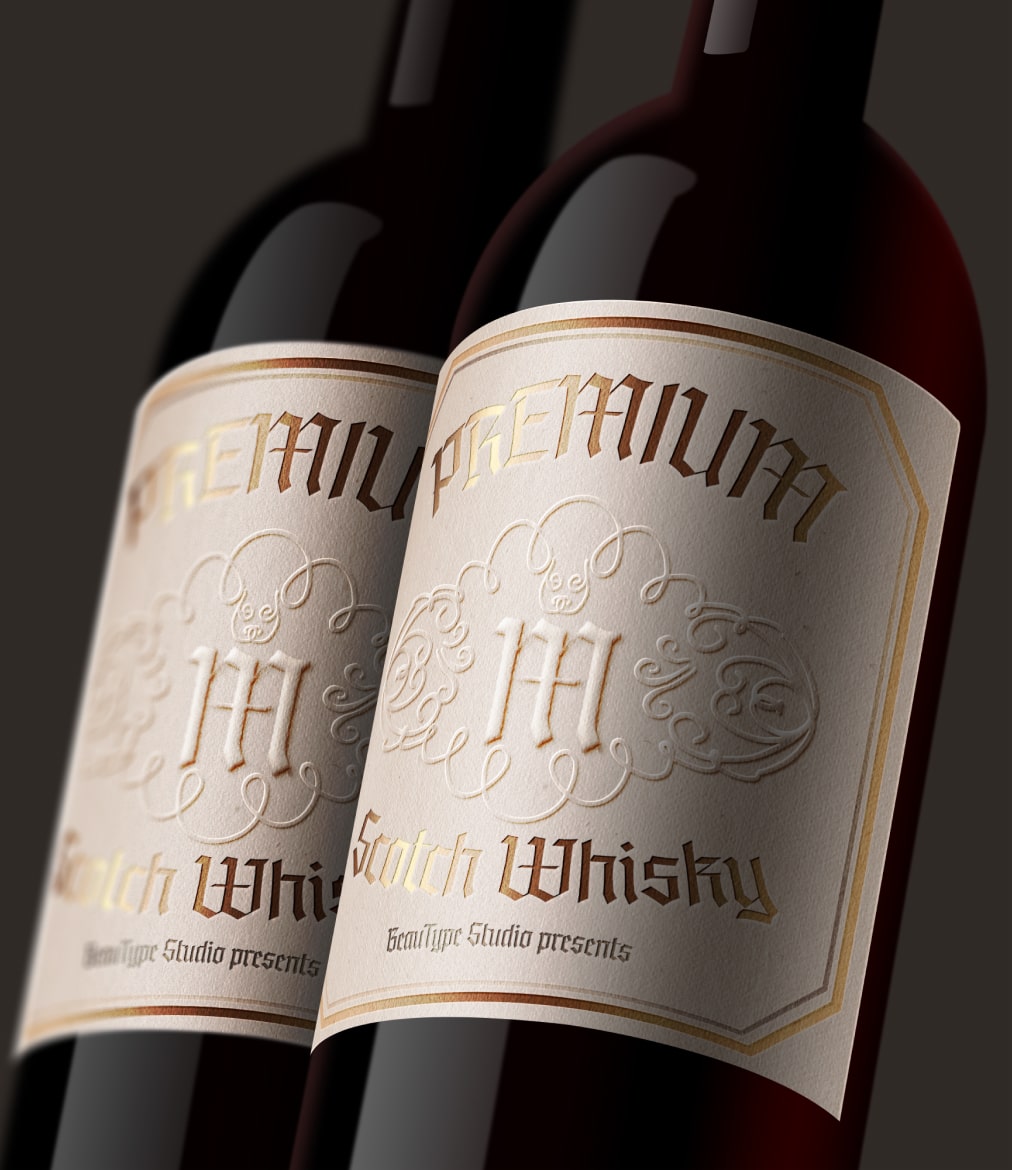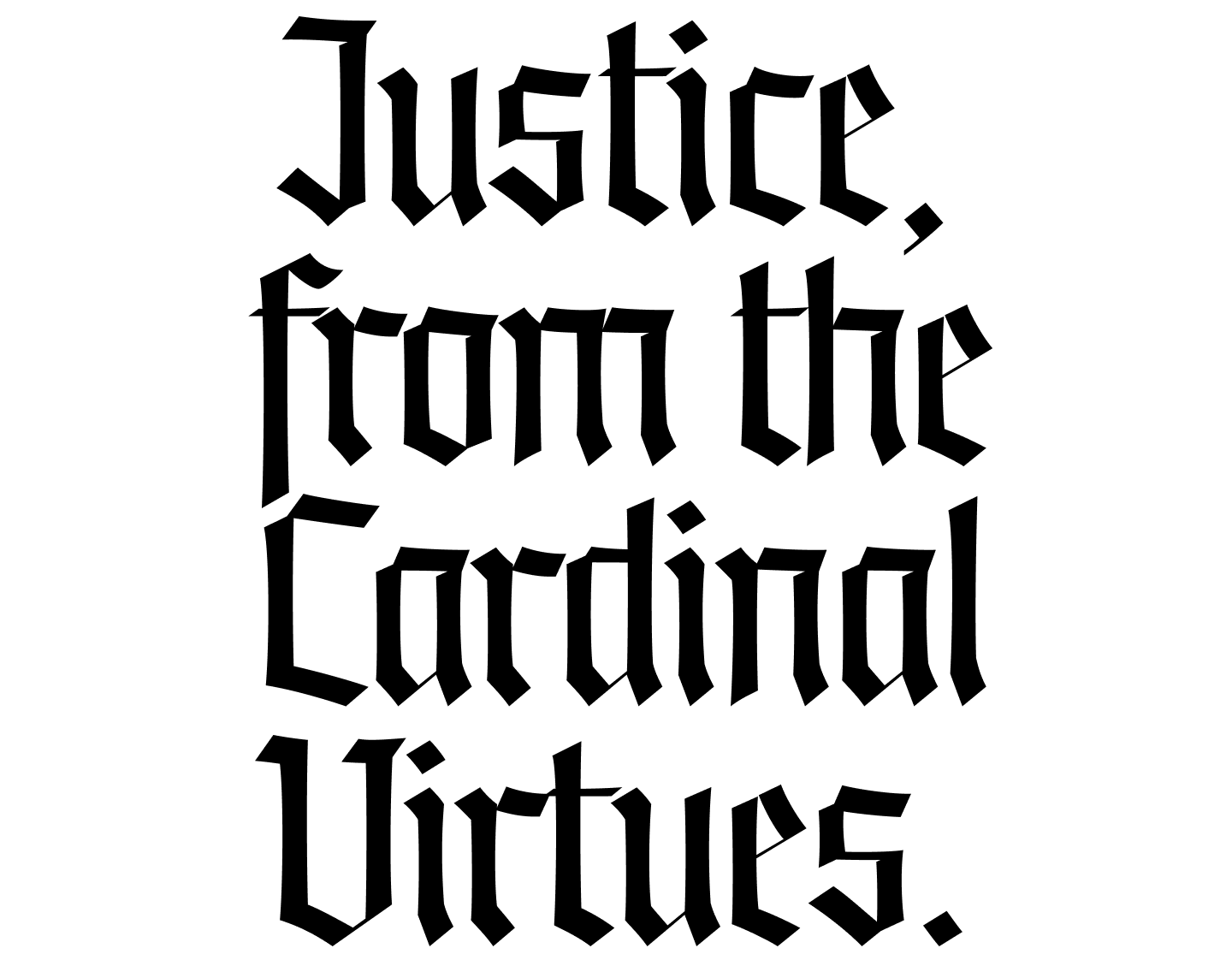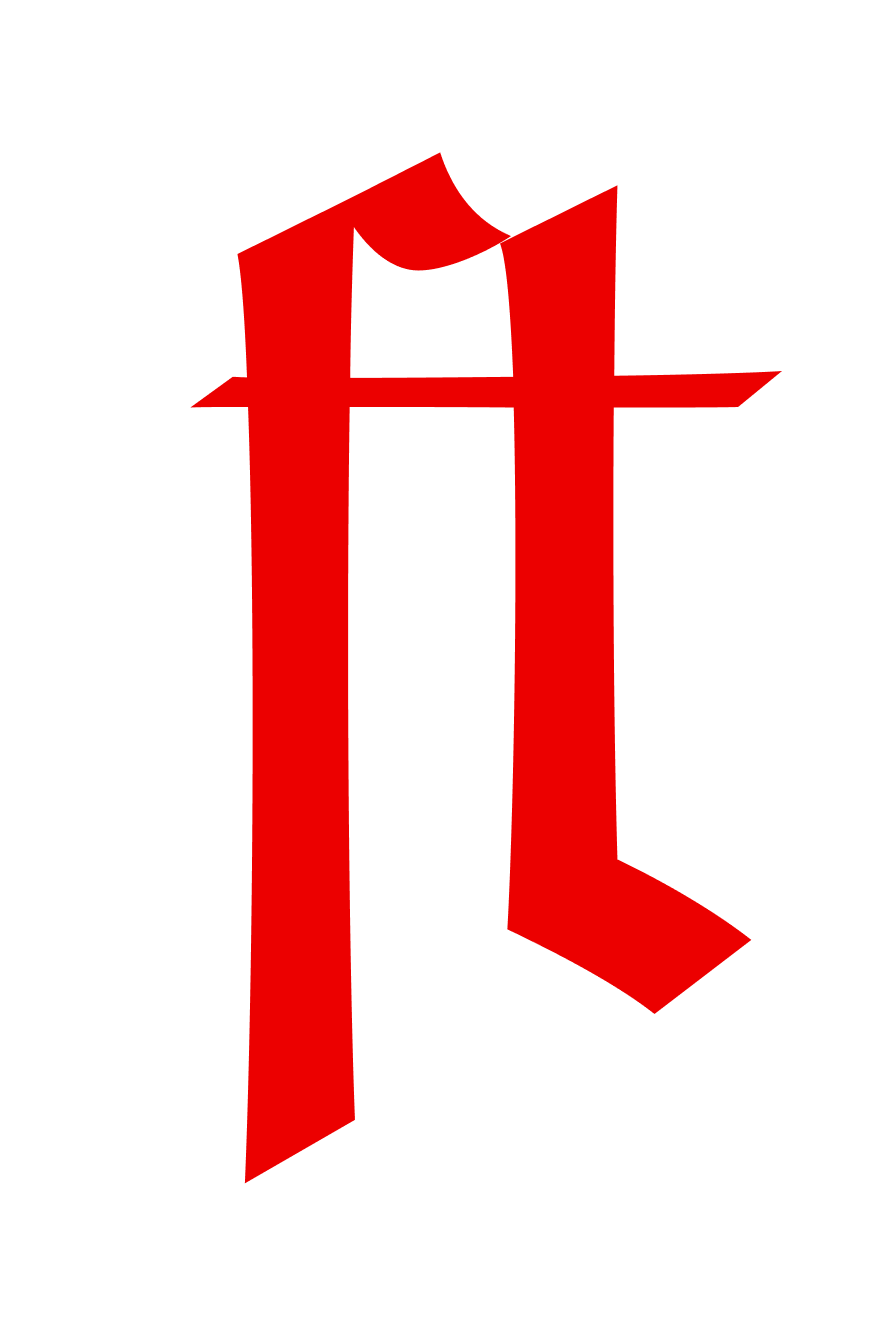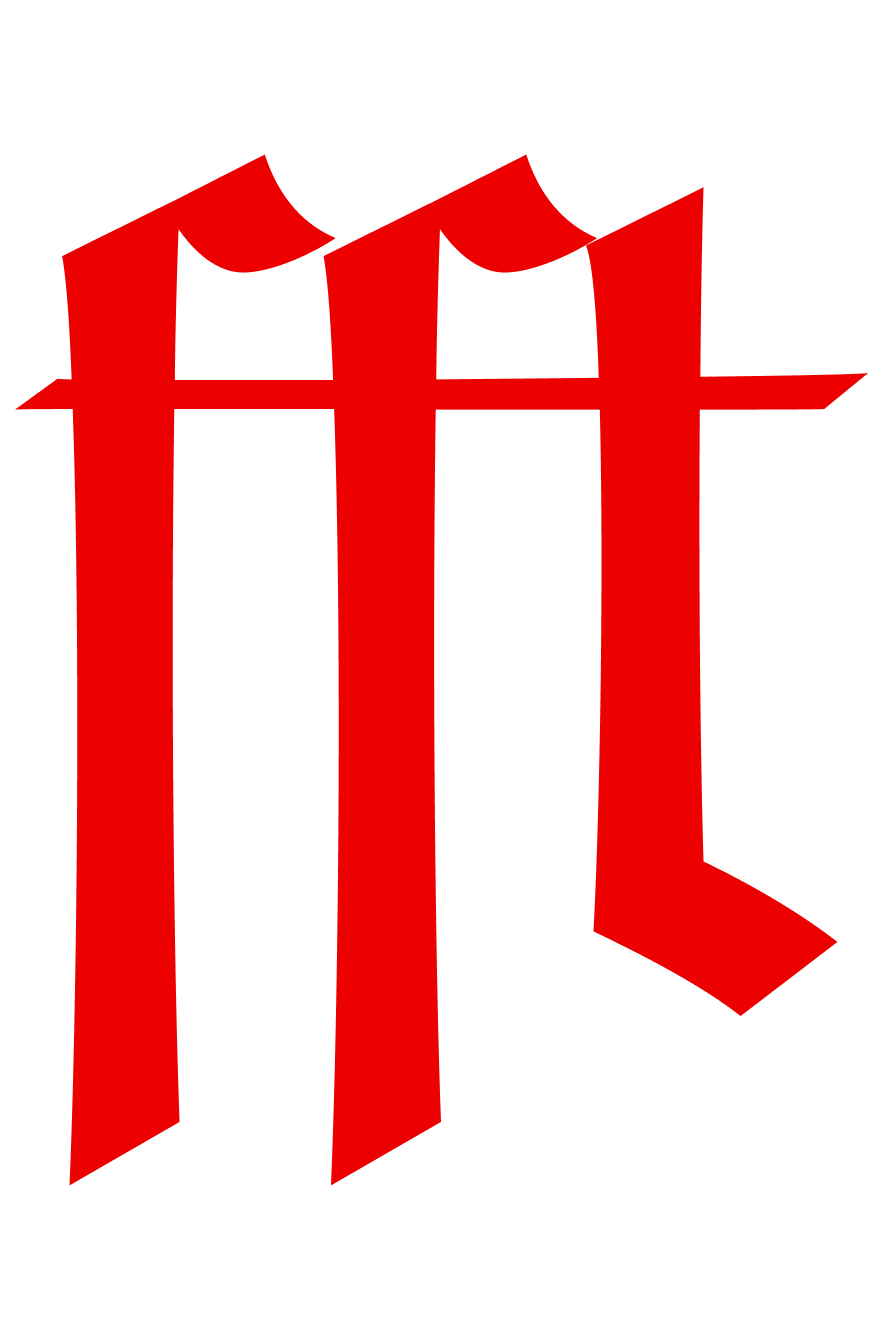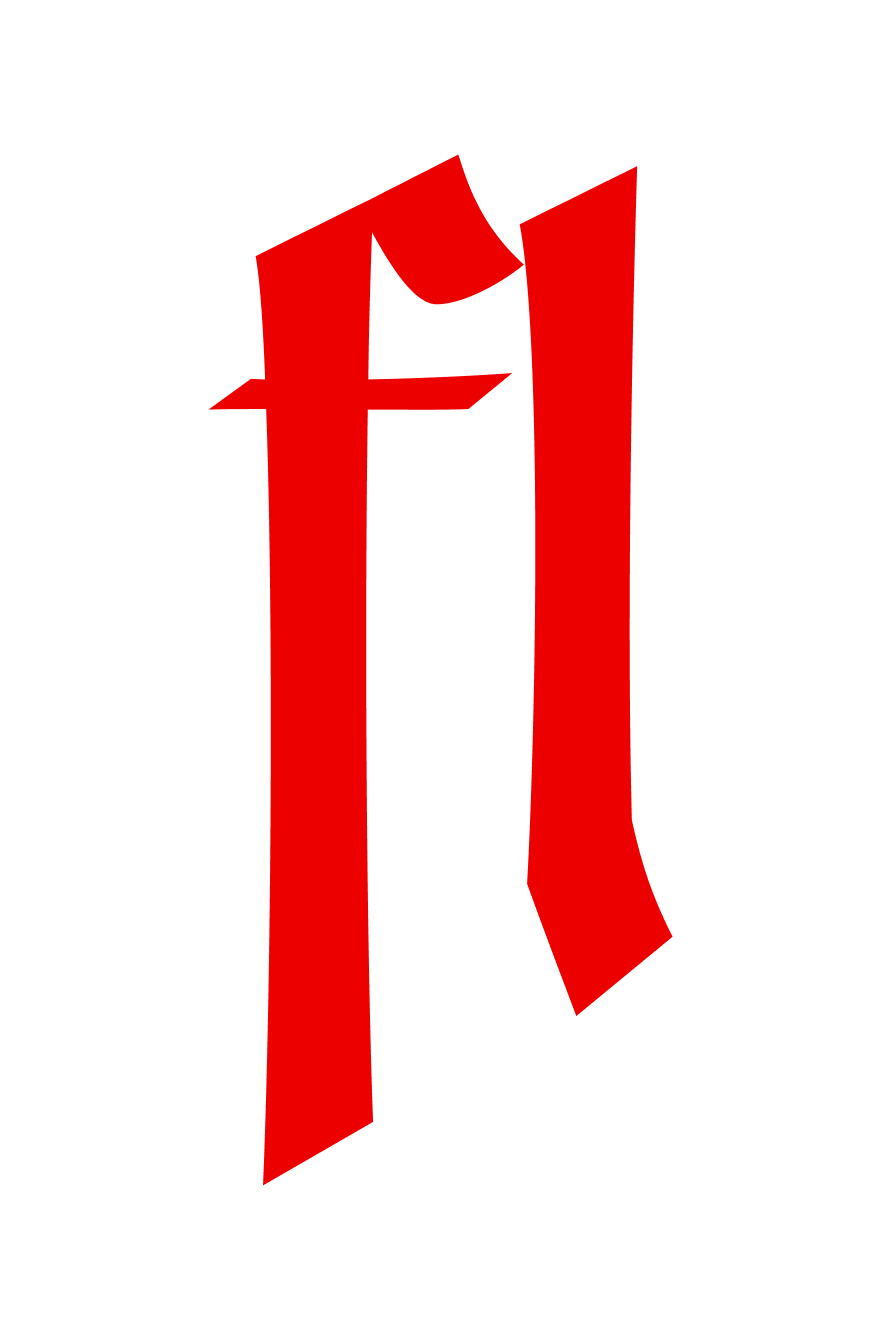
Gothic allure
Khi nghiên cứu các văn bản Kinh Thánh thời Trung Cổ, chúng tôi nhận thấy tất cả đều sử dụng Blackletter-kiểu chữ thịnh hành bậc nhất châu Âu thế kỉ XV-XVII. Hiện nay, phần lớn các typeface dựa trên Textura (một phân nhánh của Blackletter) khá cứng nhắc và máy móc trong cấu trúc. Đối với BeauType Studio, BT Noirist là một góc nhìn về Blackletter hoàn toàn mới, hiện đại xen lẫn cổ điển, giàu tính con người và tinh tế hơn.
Typeface BT Noirist
Mô phỏng lại nét bút sao cho tự nhiên nhất luôn là một trong những ưu tiên hàng đầu trong quá trình thiết kế. Cấu trúc Textura căn bản kế thừa từ Roman phần lớn được chúng tôi giữ nguyên. Thêm vào đó, các nét down-stroke có sự thay đổi nhẹ về độ dày ở đoạn giữa nhằm mô phỏng kĩ thuật pen-manipulating, tô đậm yếu tố con người hơn nguyên mẫu.
BT Noirist
Modern Blackletter Typeface
Designed by BeauType
Bên cạnh nhóm Latin cơ bản, chúng tôi cũng bổ sung thêm hệ thống dấu và kí tự tiếng Việt cho BT Noirist với 2 mục tiêu lớn: thống nhất đặc trưng thiết kế trên toàn bộ hệ thống typeface và đảm bảo khả năng nhận diện kí tự, tối ưu hóa trải nghiệm đọc.
ligatures
Ligature là một tính năng OpenType thú vị. Sử dụng ligature hợp lí sẽ tối ưu được spacing cho một số cặp kí tự khi sử dụng trong văn bản, làm cho màu khối chữ đồng đều hơn. Ngoài những sự kết hợp quen thuộc như f-t, t-t, chúng tôi cũng bổ sung thêm nhiều sự kết hợp khác vào BT Noirist như f-l, t-i, a-e,...
Character Set
Basic Latin
Vietnamese
Ligatures and alternates
Punctuation, Numerals, Currencies
bt noirist I a blackletter typeface
Reviving
Classic Charm
with a
Modern Twist